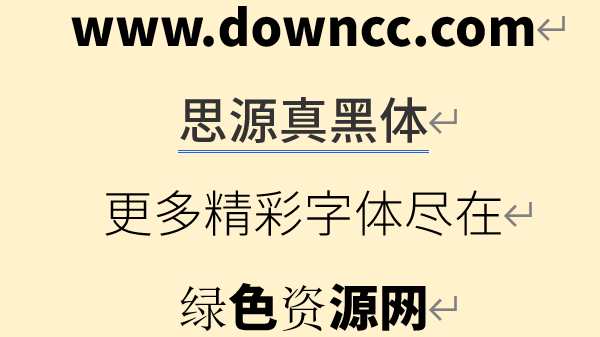
「思源真黑體」(源真ゴシック)同樣保留了思源黑體原版的優(yōu)雅以及高可讀性的特色,也是提供了7種不同的字重、3種字形樣式(包括等寬字體、比例字體)。格式上轉(zhuǎn)換成TrueType(TTF)版,細(xì)節(jié)上也做了很多的調(diào)整與變化,使得整套字體看起來更加銳利清晰,更適用于大量文字閱讀顯示、代碼編程、排版、打印等。